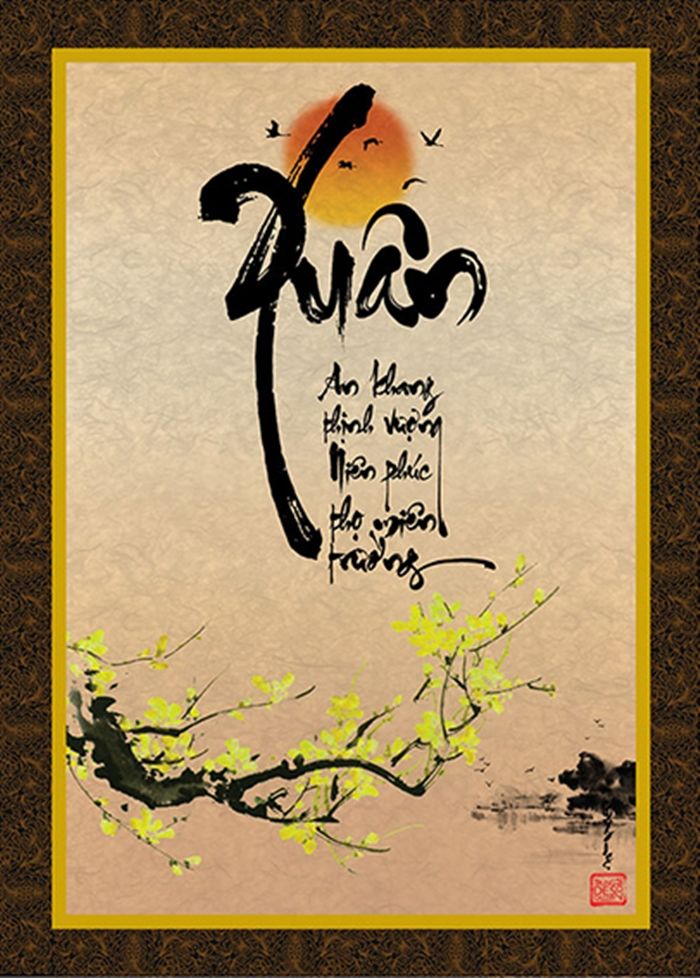
Top 10 font chữ chúc mừng năm mới full 2025
Khi Tết đến xuân về, mỗi thiết kế mang thông điệp chúc mừng năm mới cần được thể hiện một cách đặc sắc và thu hút. Font chữ chúc mừng năm mới được tạo ra để đáp ứng nhu cầu này, với các nét chữ đậm và rực rỡ, thường kết hợp hài hòa với hình ảnh lễ hội và màu sắc tươi sáng. Sự lựa chọn phong phú về kiểu chữ từ cổ điển đến hiện đại giúp người dùng dễ dàng tìm thấy phong cách phù hợp cho mọi loại ấn phẩm, từ bưu thiếp đến banner trang trí.
Top 10 font chữ chúc mừng năm mới đẹp và độc đáo mới nhất 2025
1. Chaucer Fontfont chữ chúc mừng năm mới  - Chaucer Font
2. SFU Ariston Font
3. Phông chữ UVF Memoriam Pro
4. Font chúc mừng năm mới – SVN-Motion PictureFont chúc mừng năm mới - SVN-Motion Picture
5. Font chữ chúc mừng năm mới kiểu thư pháp
Font chữ chúc mừng năm mới kiểu thư pháp
6. Font chữ chúc mừng năm mới thư pháp Đức Thủy
Font chữ chúc mừng năm mới thư pháp Đức Thủy
7. Phông chữ chúc mừng năm mới thư pháp Giao Long
Phông chữ chúc mừng năm mới thư pháp Giao Long
8. Phông chữ Chúc Mừng Năm Mới UVN
Phông chữ Chúc Mừng Năm Mới UVN
9. Font chúc mừng năm mới Rukola
Font chúc mừng năm mới Rukola
10. Font chữ chúc mừng năm mới kiểu độc đáo
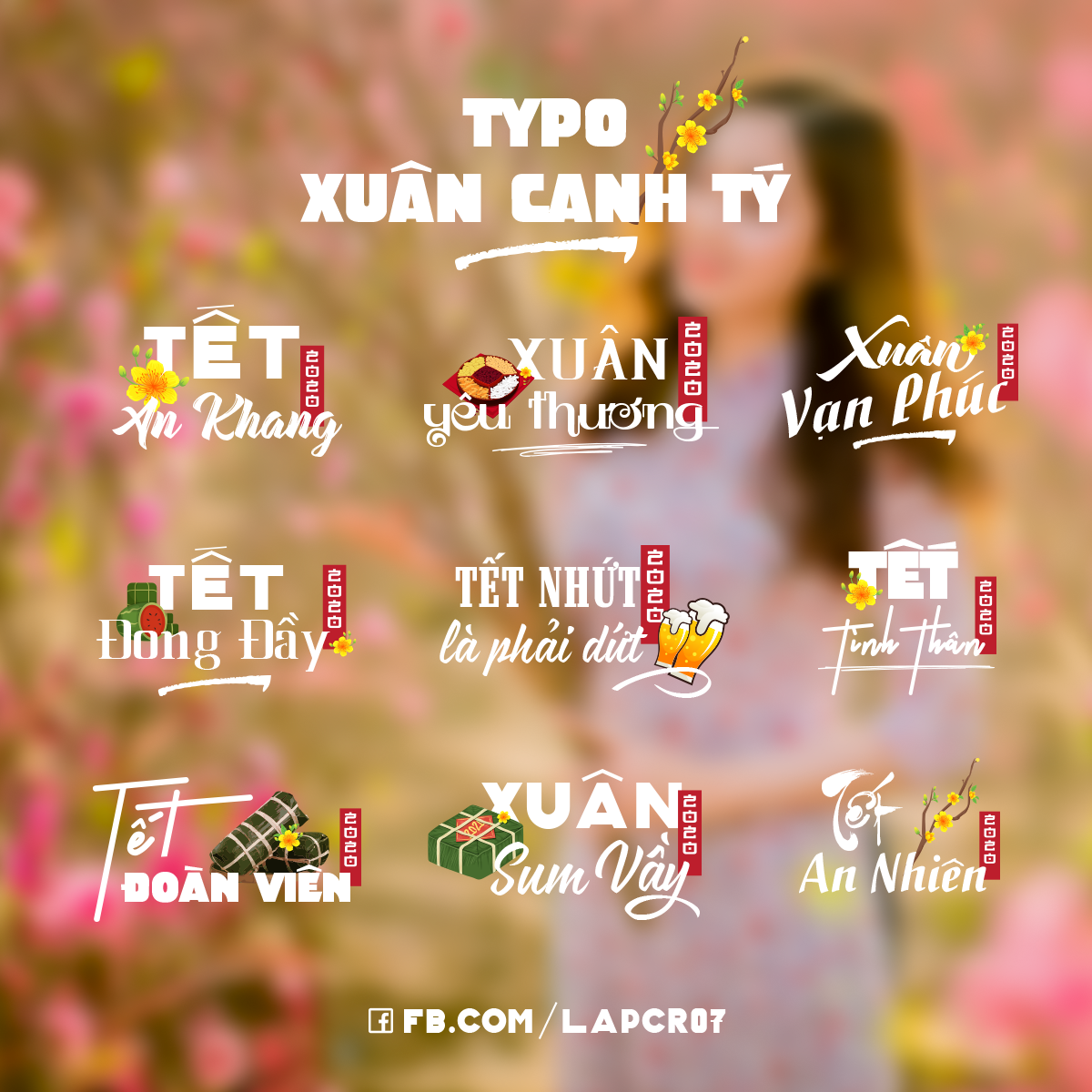Font chữ chúc mừng năm mới kiểu độc đáo